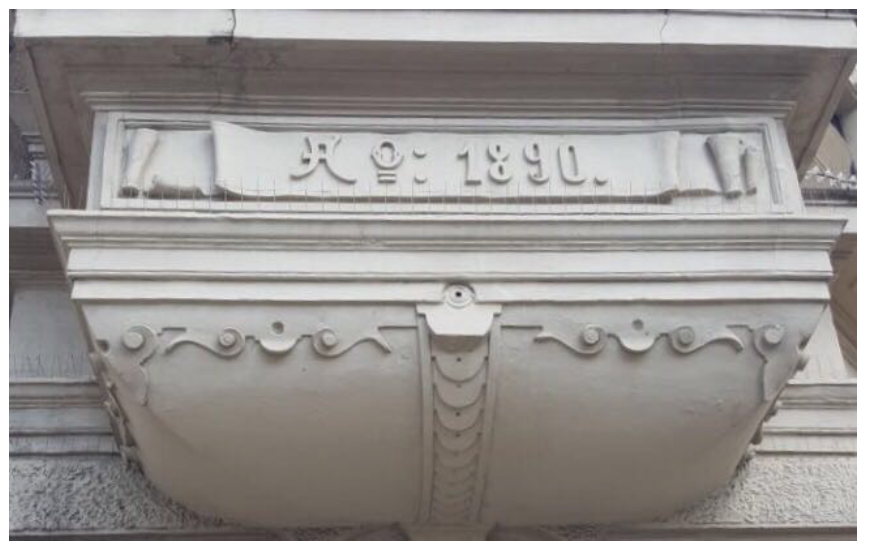
ich suche ein Zeichen. Ihr seht es im angehängten Bild - das Erste ist es. Was bedeutet es?
Hat jemand eine Idee? Gibts das als Schrift?
Ich vermute eine Abkürzung für "Anno", also fürs Baujahr.
Das º wird hier aber nicht als Ordinalzeichen verwendet.
Aber eben in missverstandener Analogie zur damals gebräuchlichen Abkürzung Nº für Nummer, da könnte man das wohl auch für Anno auch als Aº verwenden, eigentlich falsch und recht unüblich, aber irgendwie pragmatisch und aus dem Zusammenhang auch ableitbar.
Das º in Numero ist aber kein Ordinalzeichen zum N, vielmehr ist № ein eigenes Zeichen (U+2116 numero sign), das gern mit tropfenförmigen Serifen versehen wurde.
Wenn ein eigenständiges Aº entworfen würde, fände ich das als offizielle Abkürzung für Anno eigentlich ganz charmant.